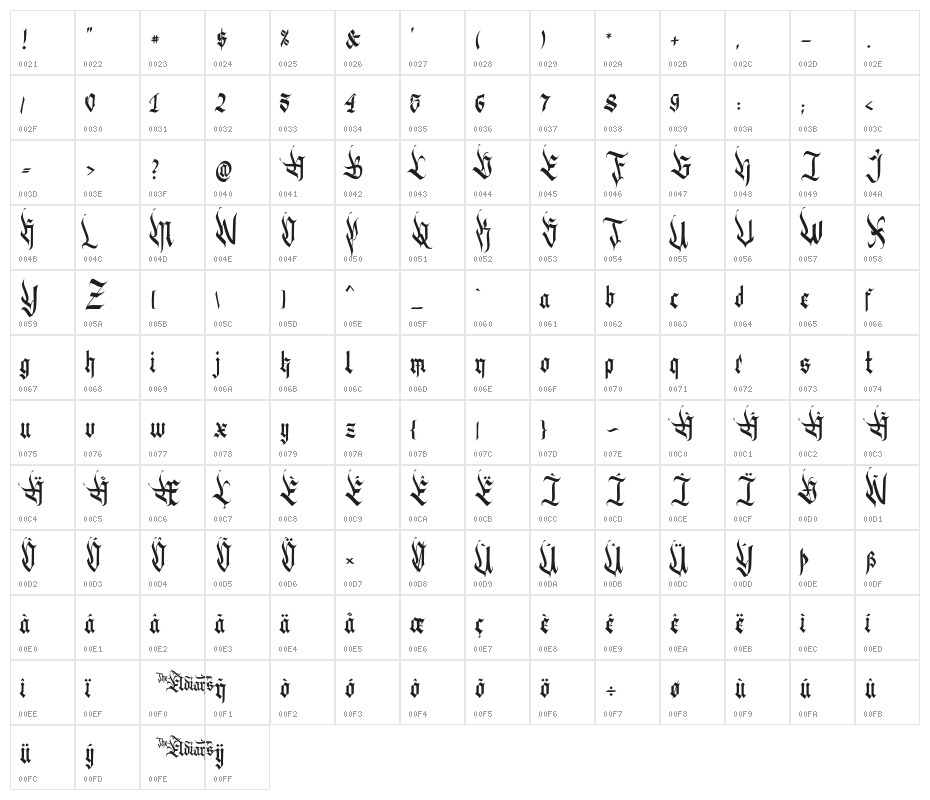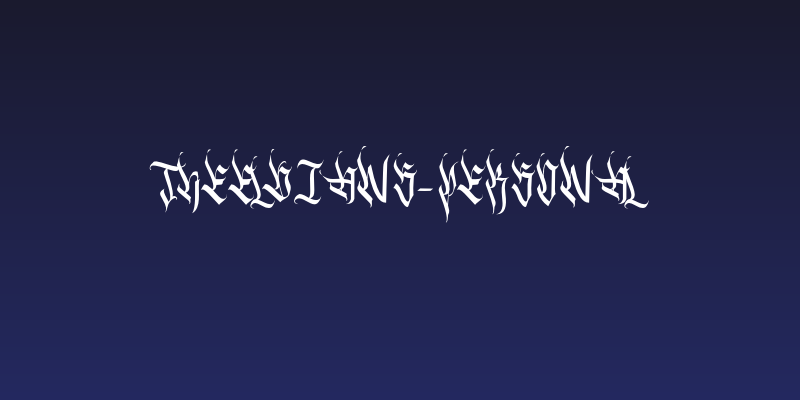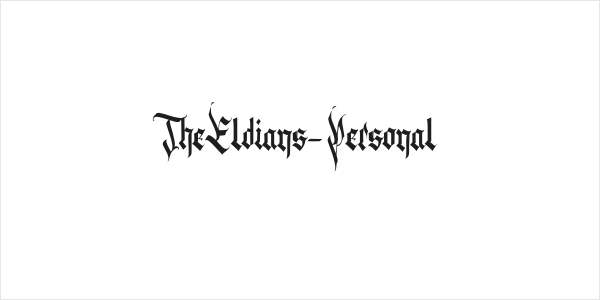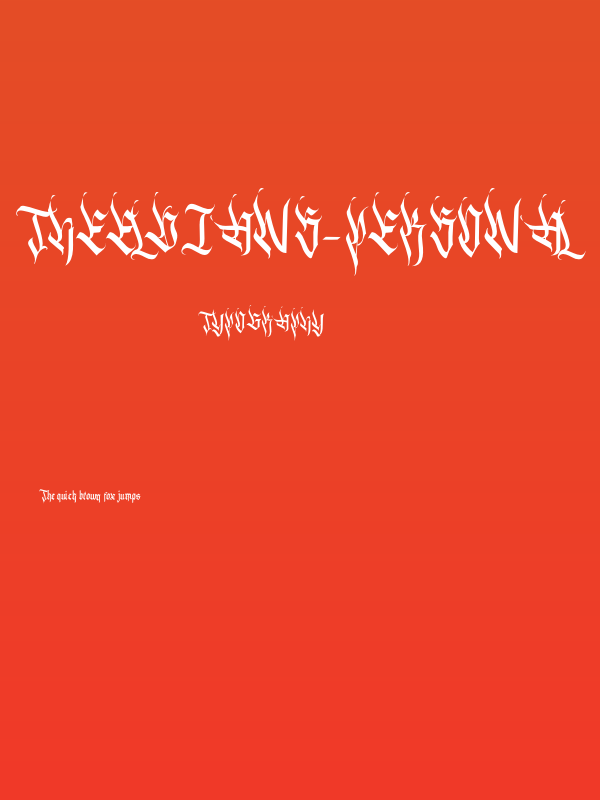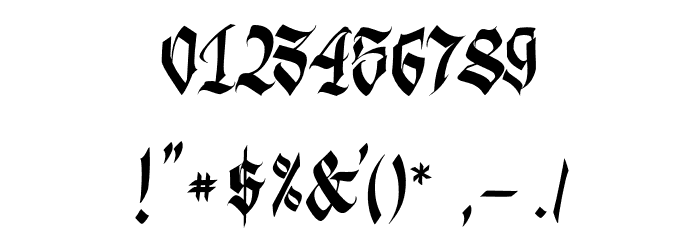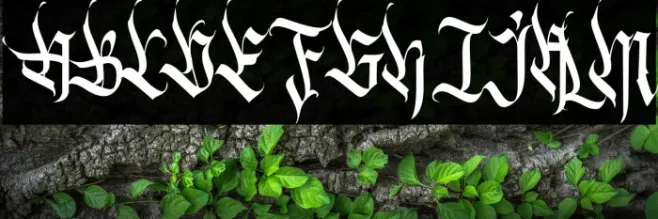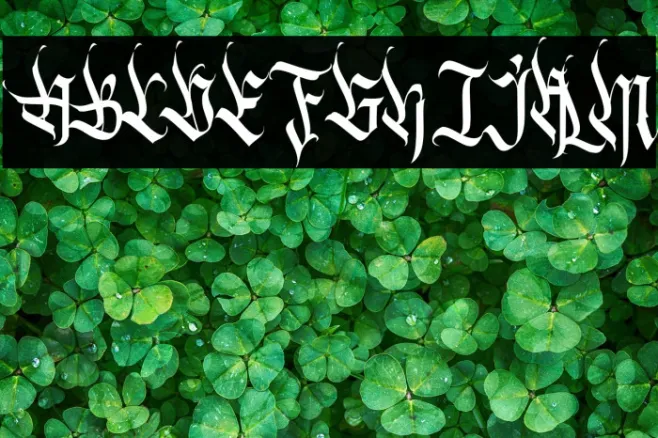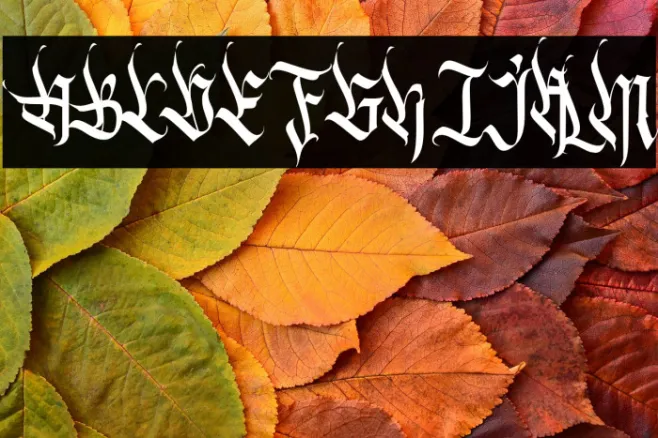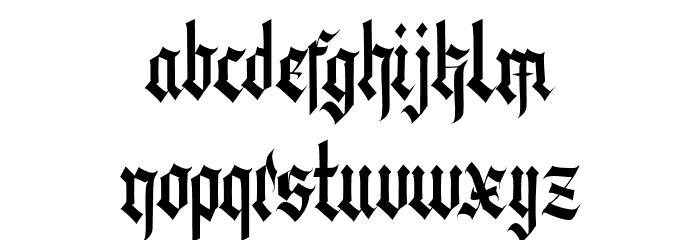
TheEldians-Personal Font
✎ Gothic
| Schriften Familie | The Eldians |
| Kategorien | Gothic |
| Gesamtstil | Vintage |
| Anwendungsfall | Logos, Headlines, Decorative text |
| Vorgeschlagene Projekte | Suitable for use in historical themed projects, book covers, posters, and branding that requires a gothic or medieval touch. |